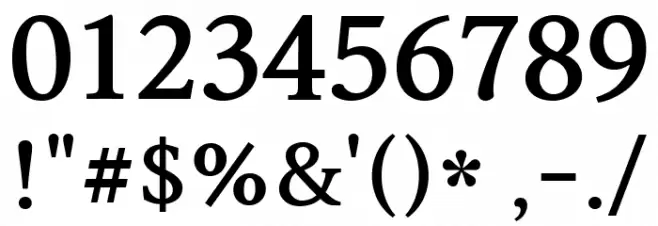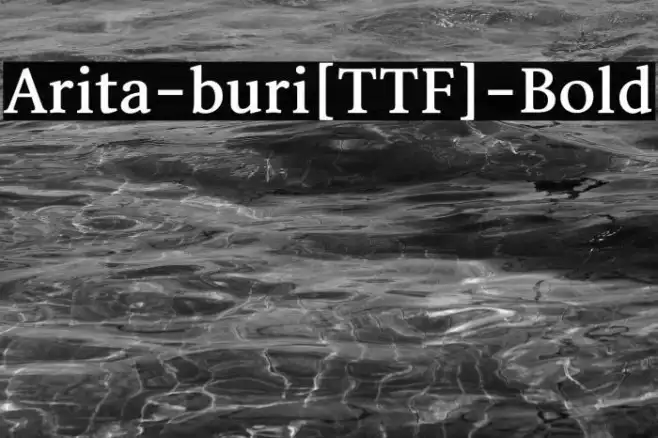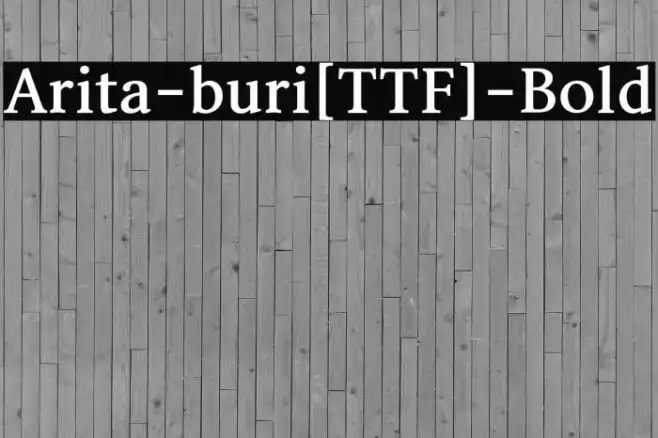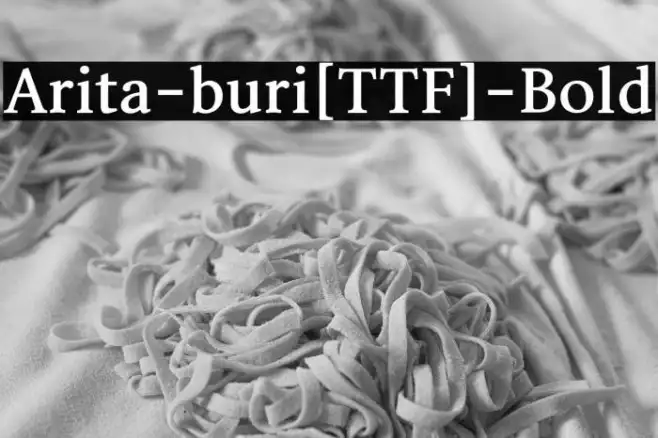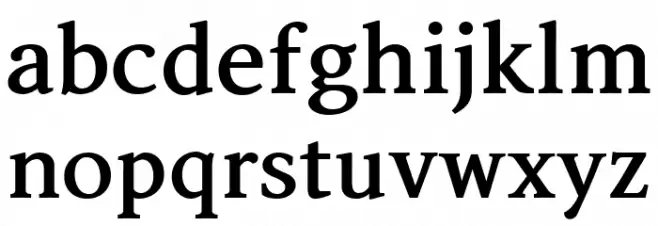
Arita-buri[TTF]-Bold Font
✎ Serif
| Gesamtstil | Classic |
| Vorgeschlagene Projekte | Ideal for editorial design, book covers, formal invitations, and branding materials that require a traditional yet bold appearance. |